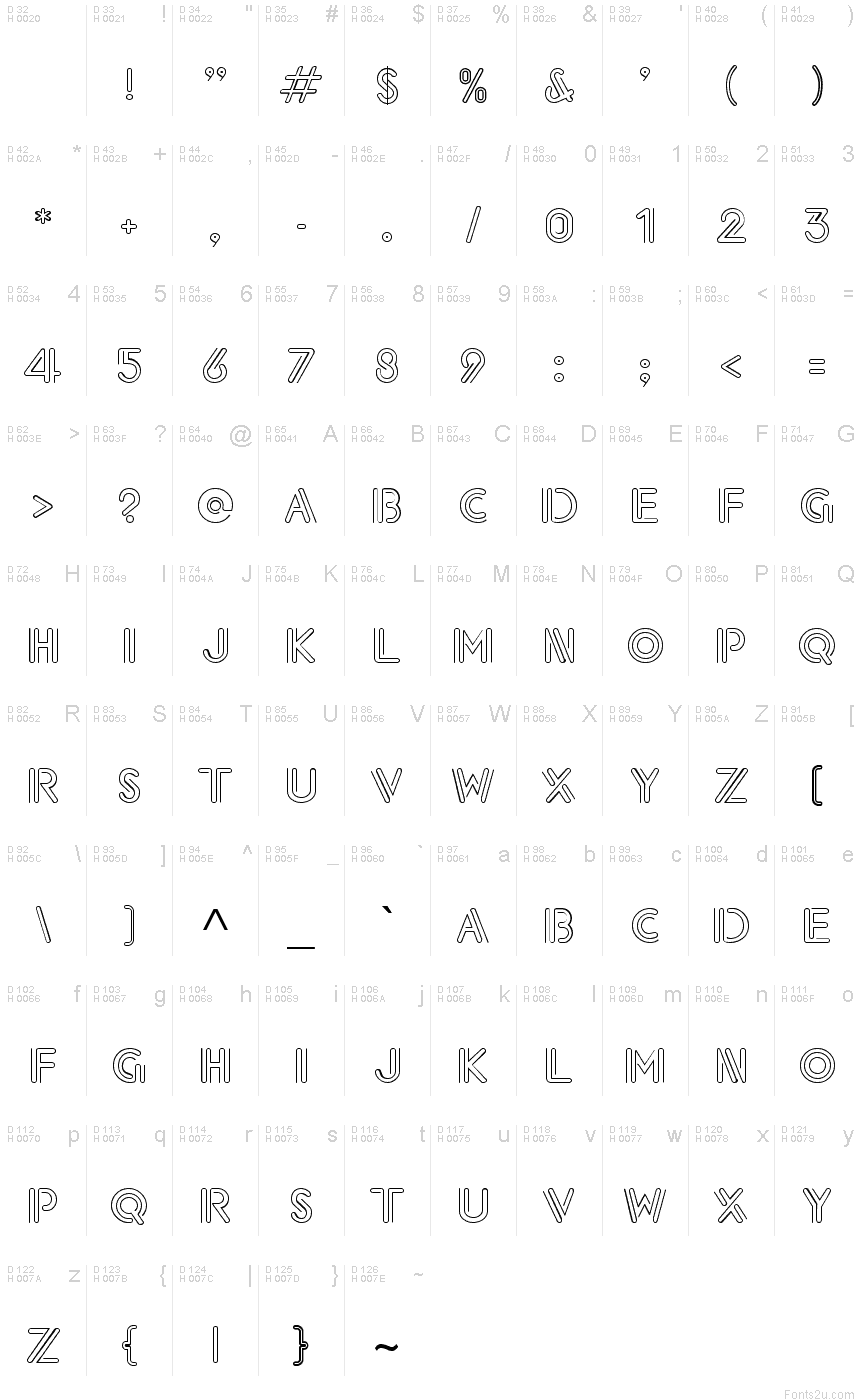
Paperclip è un font display gratuito e dal gusto "groovy" di Brøderbund Software. Ogni lettera è trasformata in un profilo tubolare curvo che ricorda un filo di metallo o la plastica modellata. Questa costruzione a linea singola conferisce all'alfabeto un ritmo vivace e aperto, con angoli arrotondati e spazi stretti che mantengono le forme decorative senza risultare troppo cariche.
Perfetto per titoli brevi, volantini per eventi, packaging retrò, poster musicali e grafiche per negozi. Questo font ha una personalità decisa, ideale anche per loghi e titoli, specialmente quando cerchi una resa grafica leggera e dall'aspetto artigianale, anziché solida o compatta.